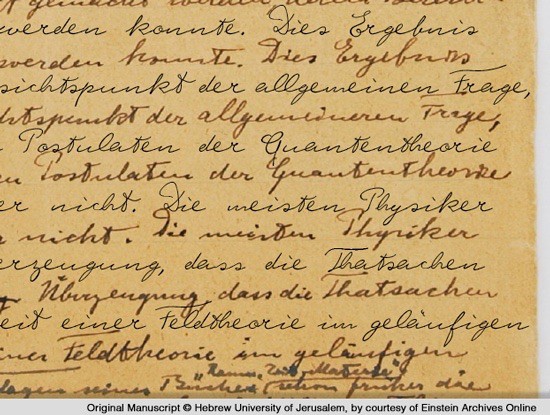
Специалист по типографике из Германии планирует создать набор шрифтов, повторяющих почерк известных личностей. На Kickstarter он запустил сбор средств на создание шрифта, за основу которого взят почерк Альберта Эйнштейна.
Типограф из Франкфурта Харальд Гайслер (Harald Geisler) решил создать серию шрифтов, которые повторяли бы почерк известных личностей. Гайслер заявил, что вдохновился этой идей от простой записки на салфетке, написанной в кафе.
Начиная с 2009 года Харальд Гайслер вместе со своей сподвижницей Элизабет Уотерхаус (Elizabeth Waterhouse) работает над проектом, находя сотни страниц с почерком Эйнштейна и создавая цифровые копии каждой рукописной буквы.
Каждую литеру приходится прорисовывать несколько раз, так как при написании они могут отличаться по размеру и стилю. Гейслер уже создал по одному варианту каждой буквы.
Запущенный им на Kickstarter проект позволит собрать необходимые средства для реализации проекта, включая разнообразные шрифты, основанные на почерке различных известных людей, и варианты их написания.
В 2013 году типограф уже занимался подобным проектом на Kickstarter, в рамках которого он создал шрифт, имитирующий почерк Зигмунда Фрейда. Для каждой литеры он нарисовал четыре разных варианта, так что при наборе текста они чередовались, создавая ощущение рукописи. Пользователи пожертвовали ему более 25 тысяч долларов.
Эту же технику Гейслер собирается повторить в создании шрифта с почерком Эйнштейна. Один вариант начертания букв у него уже готов, однако финансирование проекта позволит ему потратить ещё шесть месяцев на создание трёх других вариантов отображения символов.
Да у него же почерк, как у врача.
Работает с 2009 года имеет по 1 варианту буквы, то есть 28? Я не эксперт в шрифтоделии, но как-то это не густо.
представляю шрифт на компе как у врача))) это же ужас